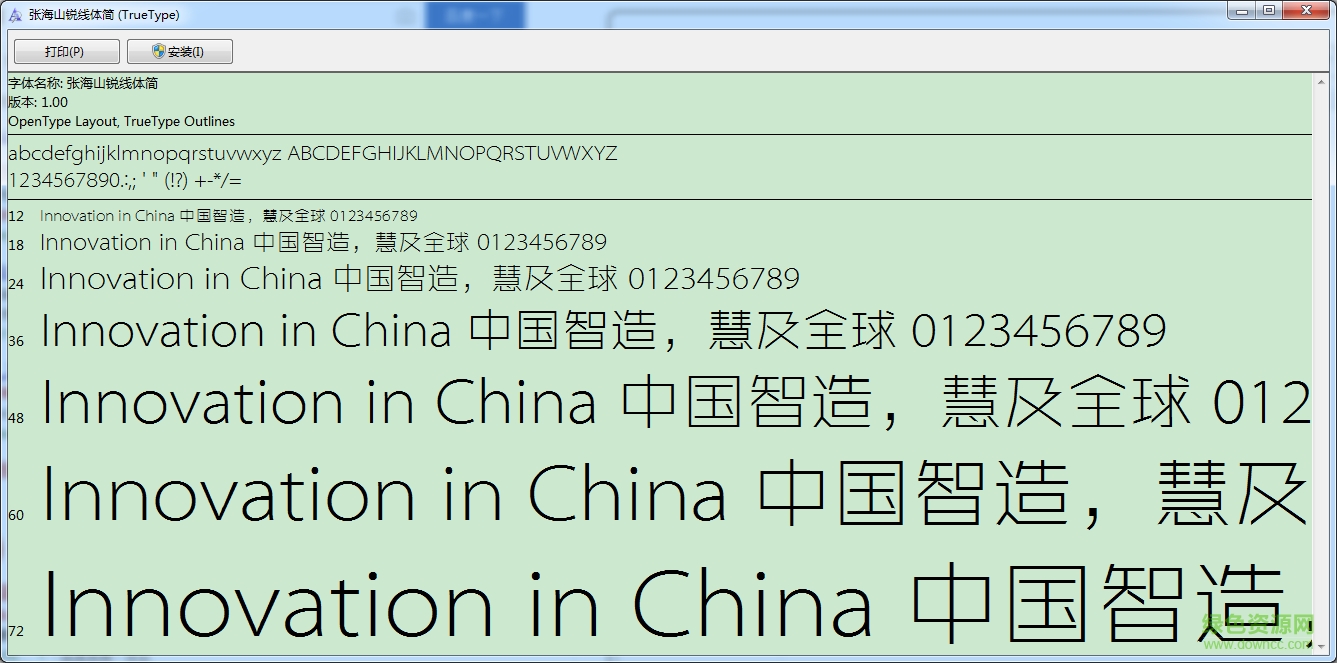
zhsrxt gbk1 0
zhsrxt gbk1 0是什么字體?zhsrxt gbk1 0即為張海山銳線體簡字體,字體大方得體,支持漢字、中文、英文等多種方式輸入顯示,一鍵安裝便可使用,極具美感時刻彰顯個人魅力。快來綠色資源網(wǎng)下載體驗吧!
zhsrxt gbk1 0字體介紹
本字體是一款優(yōu)秀的藝術(shù)漢字字體,張海山銳線體簡是根據(jù)書法家張海山的書法作品制作的字體,本字體具有筆畫清晰纖細的優(yōu)點,多用于廣告設(shè)計等用途。